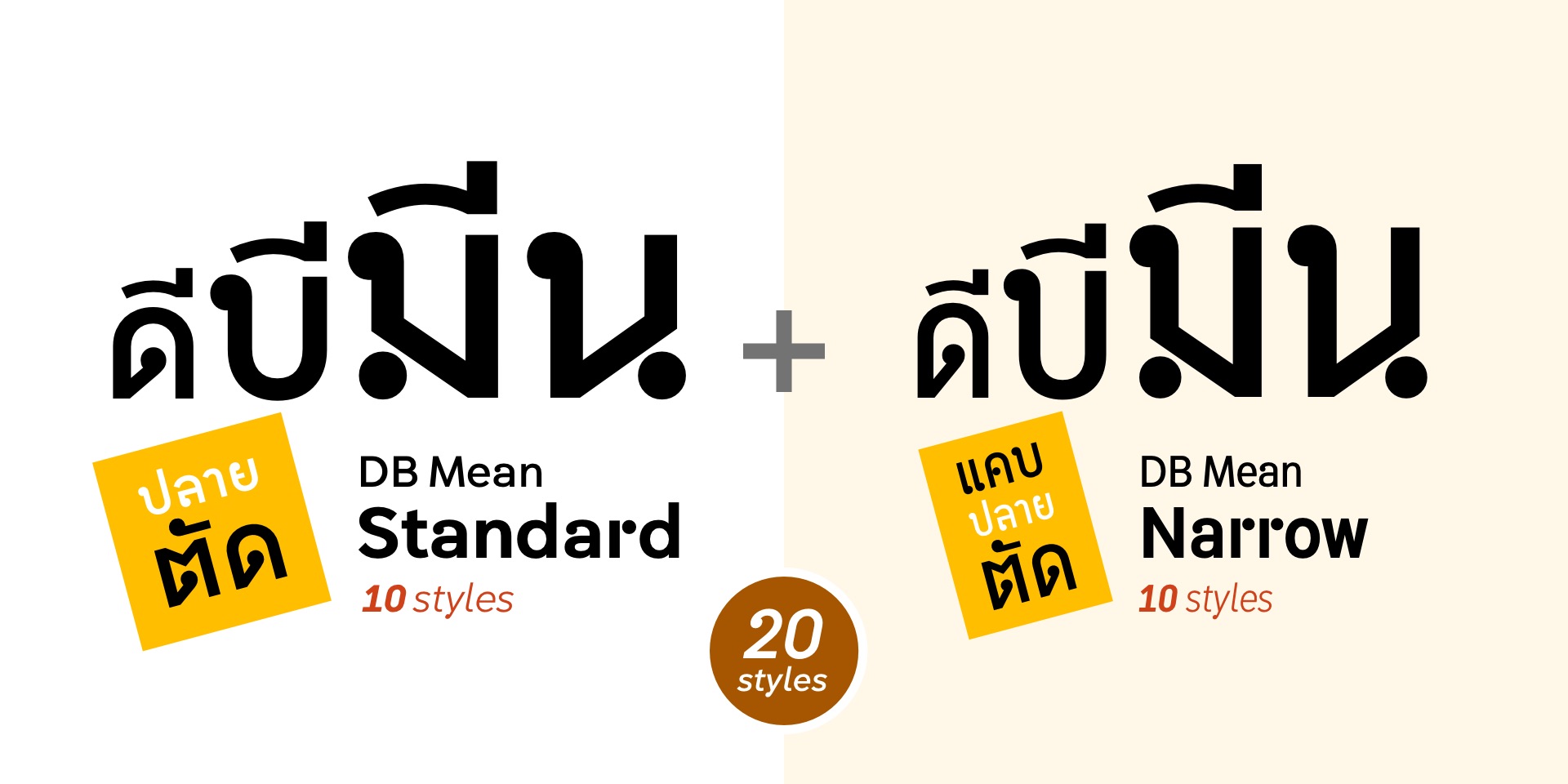
DB Mean Bundle
ดีบี มีน ปลายตัด
2 font families,
20 styles
รวมชุด ฟอนต์
DB Mean และ DB Mean Narrow
ตัวกว้างปกติและตัวแคบ
ที่เป็นตัวพาดหัวก็ได้ เป็นตัวพื้นก็ดี